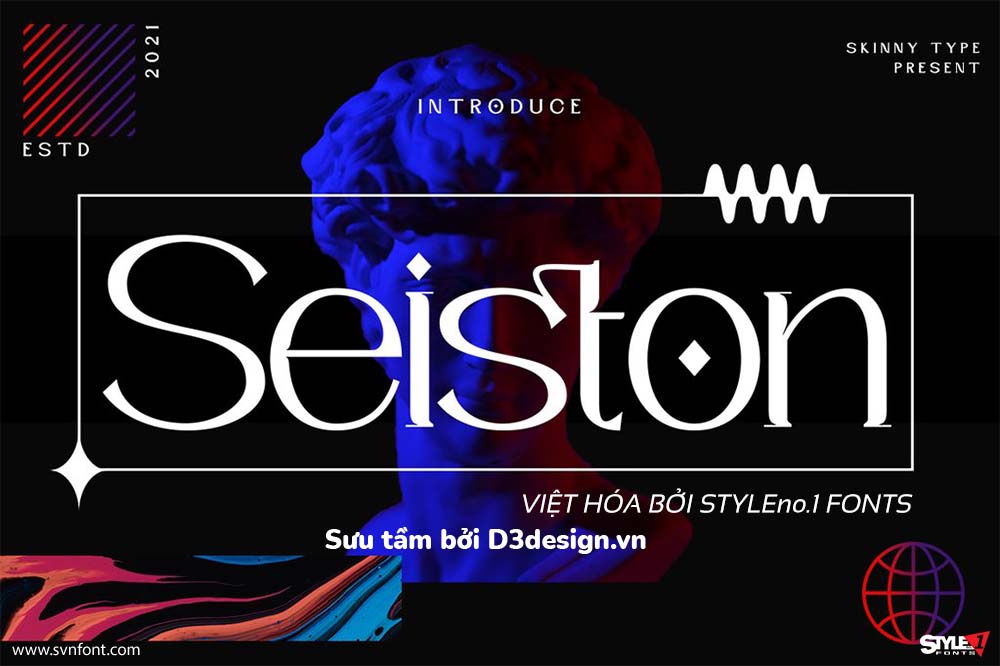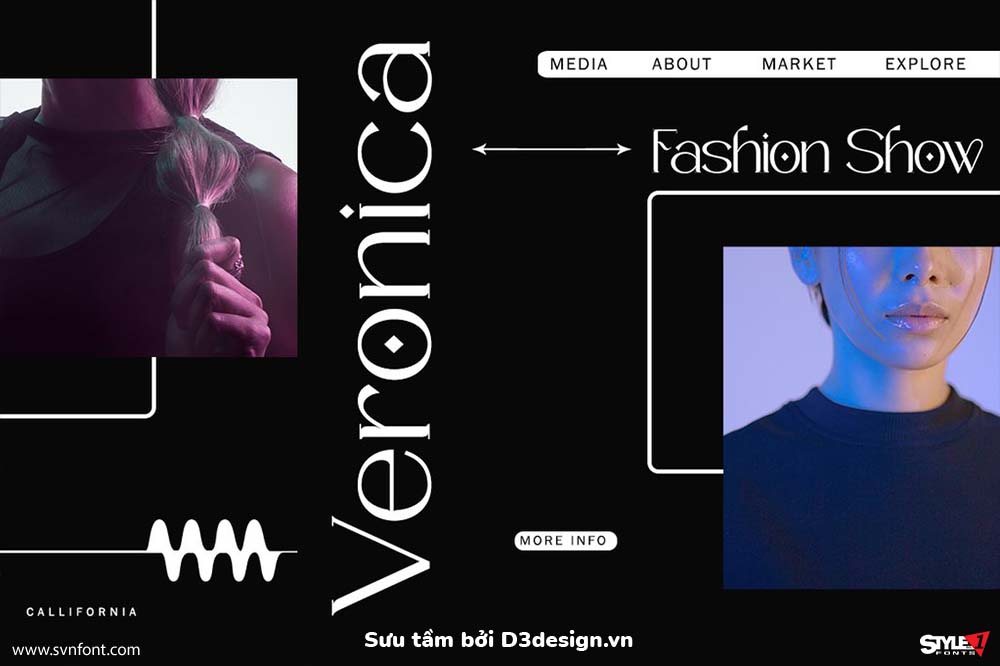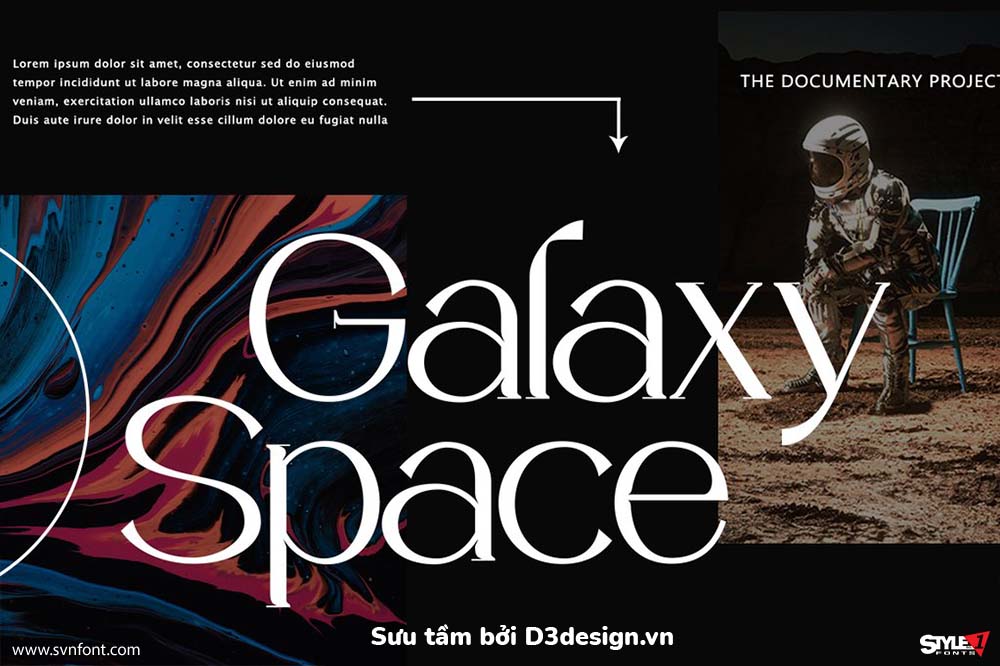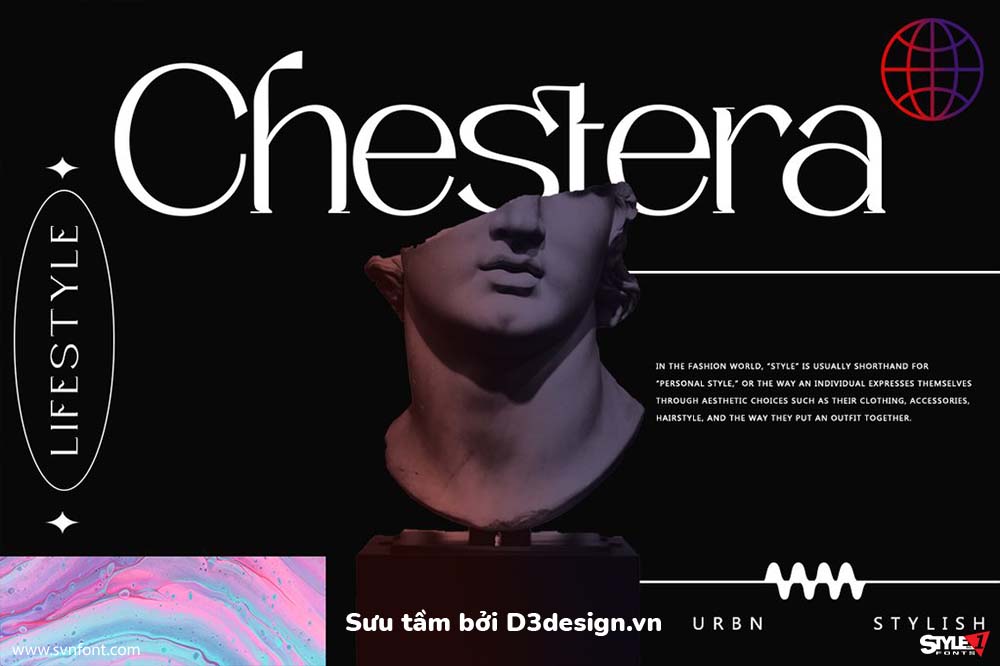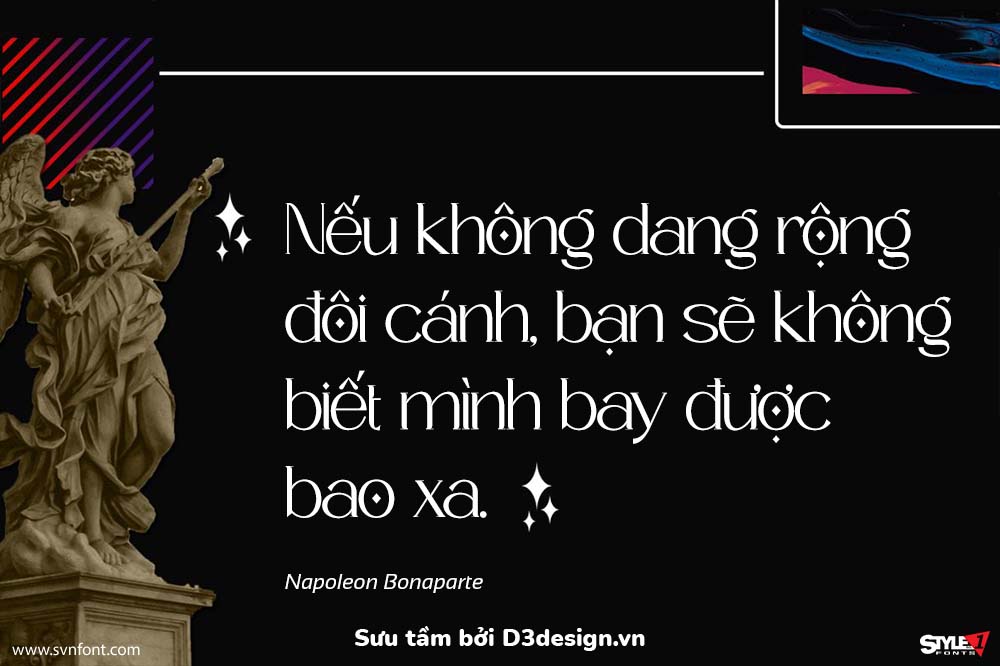
Font Việt Hóa SVN- Seiston Mang Phong Cách Hiện Đại Mới
Giới thiệu Seiston, một font hiện đại mới, hoàn hảo cho dự án xây dựng thương hiệu tiếp theo của bạn.
Nhà thiết kế: Muhajir Muhajir
Nhà phát hành: Skinny Type
Việt hóa: STYLEno.1 Fonts